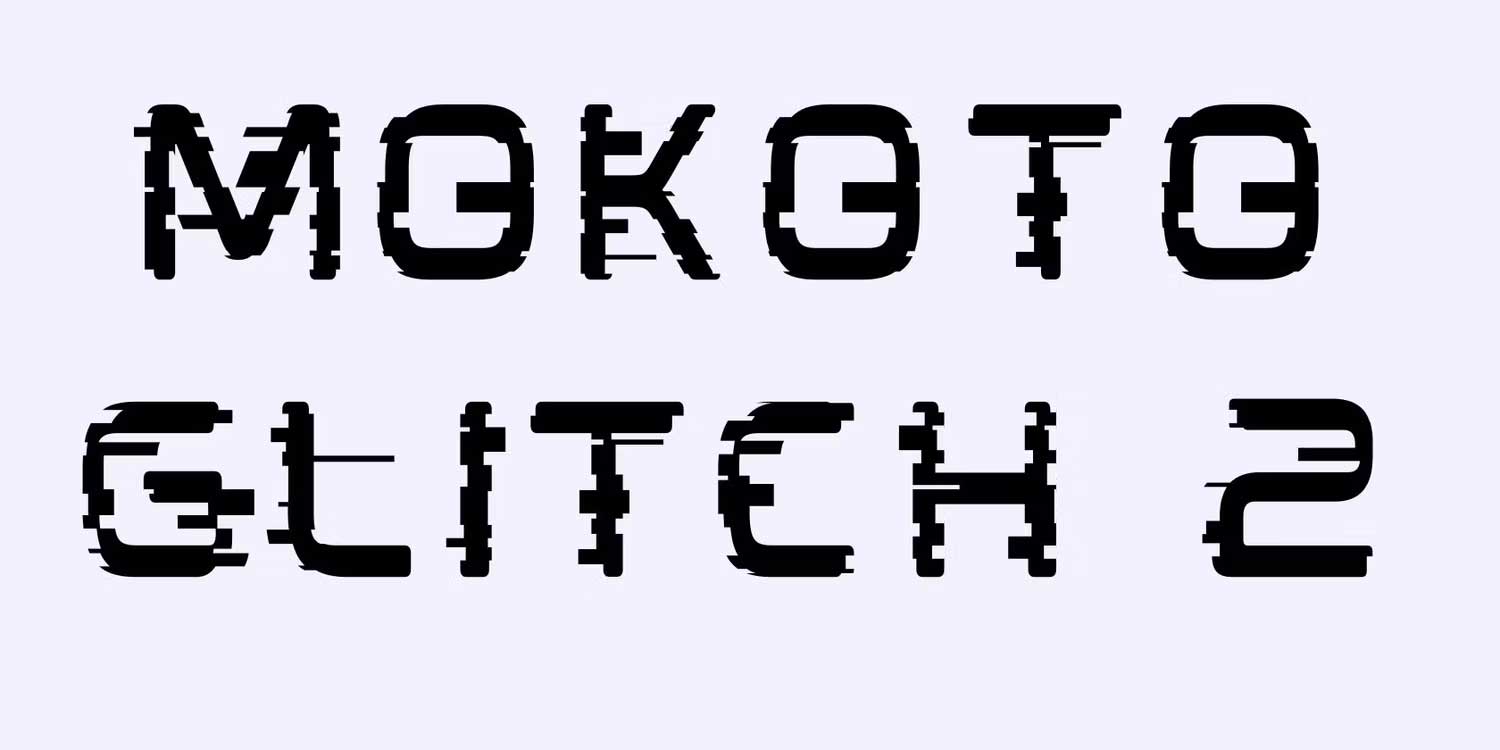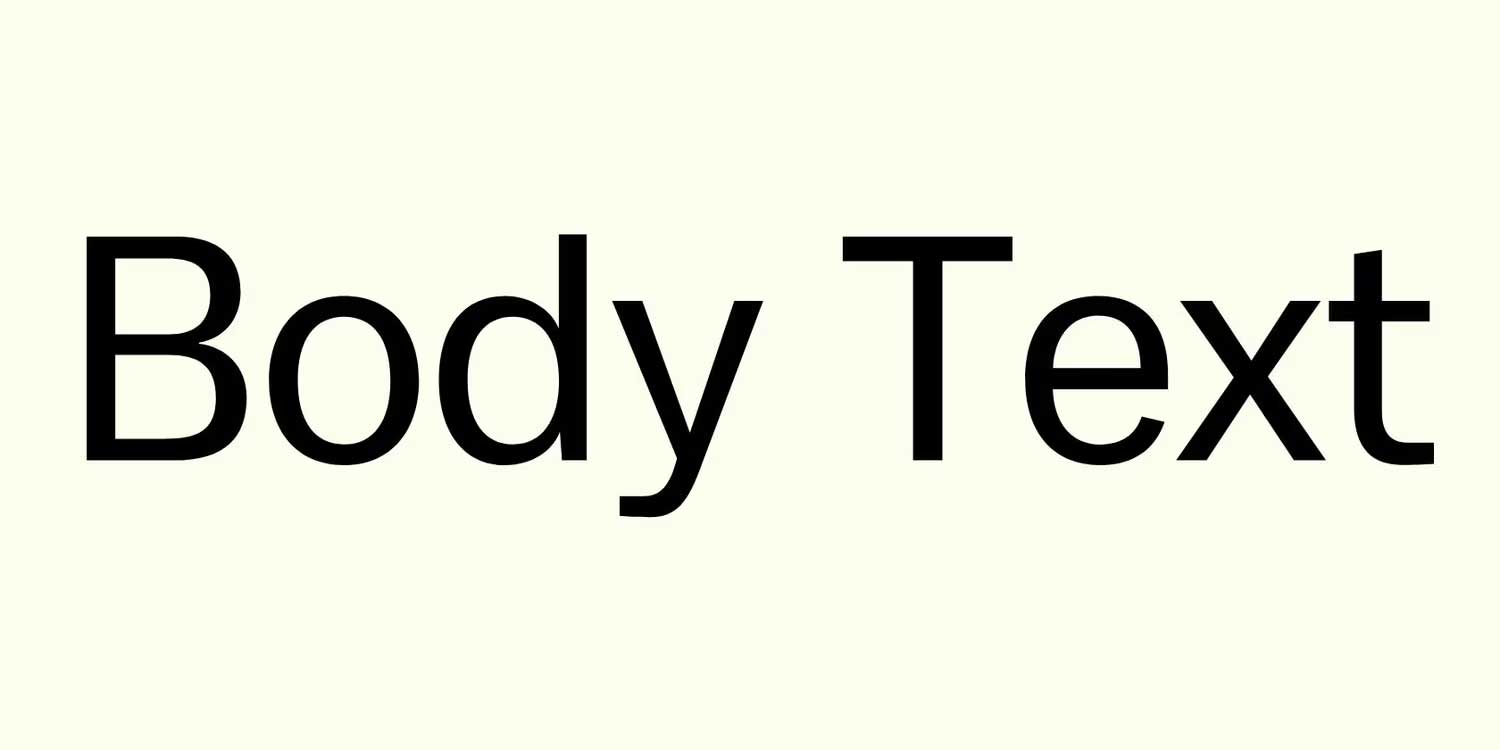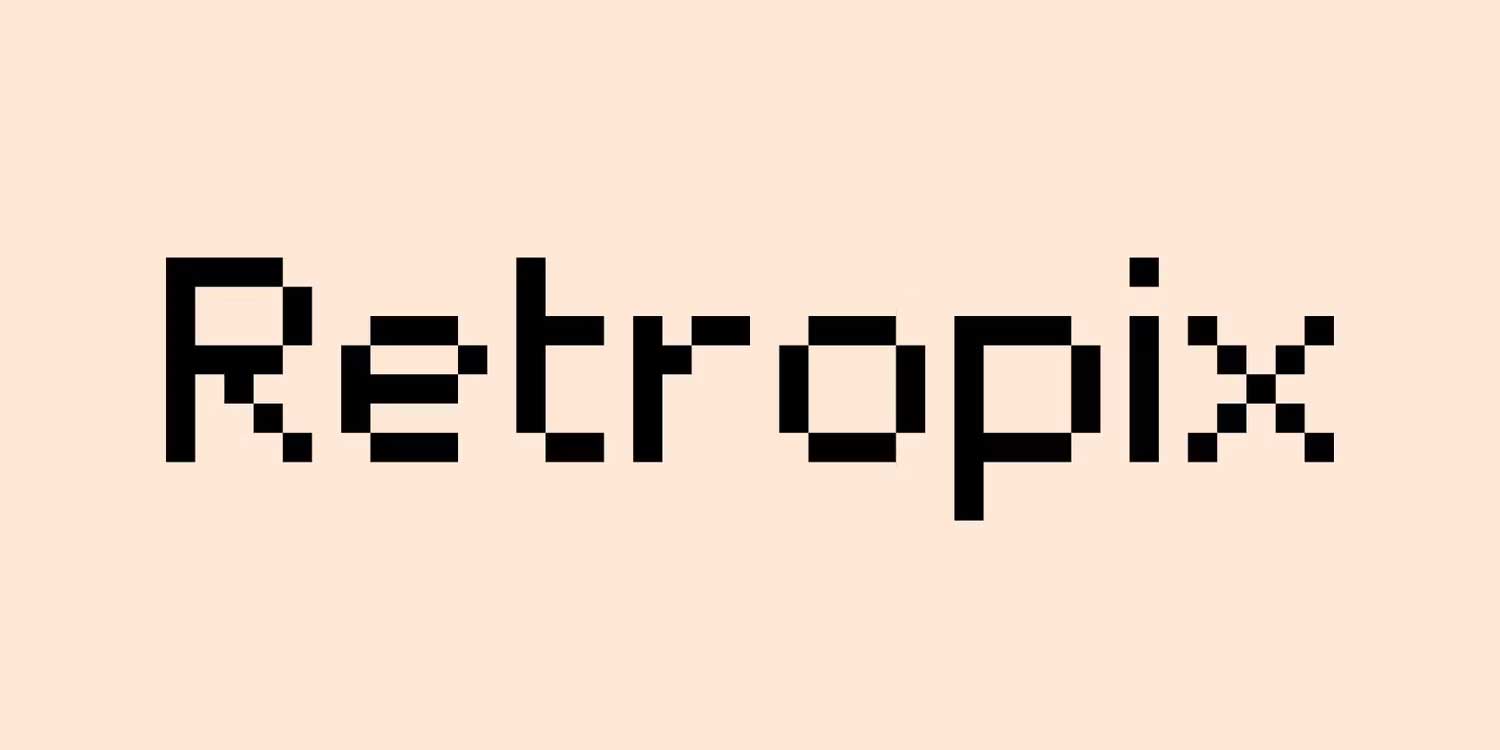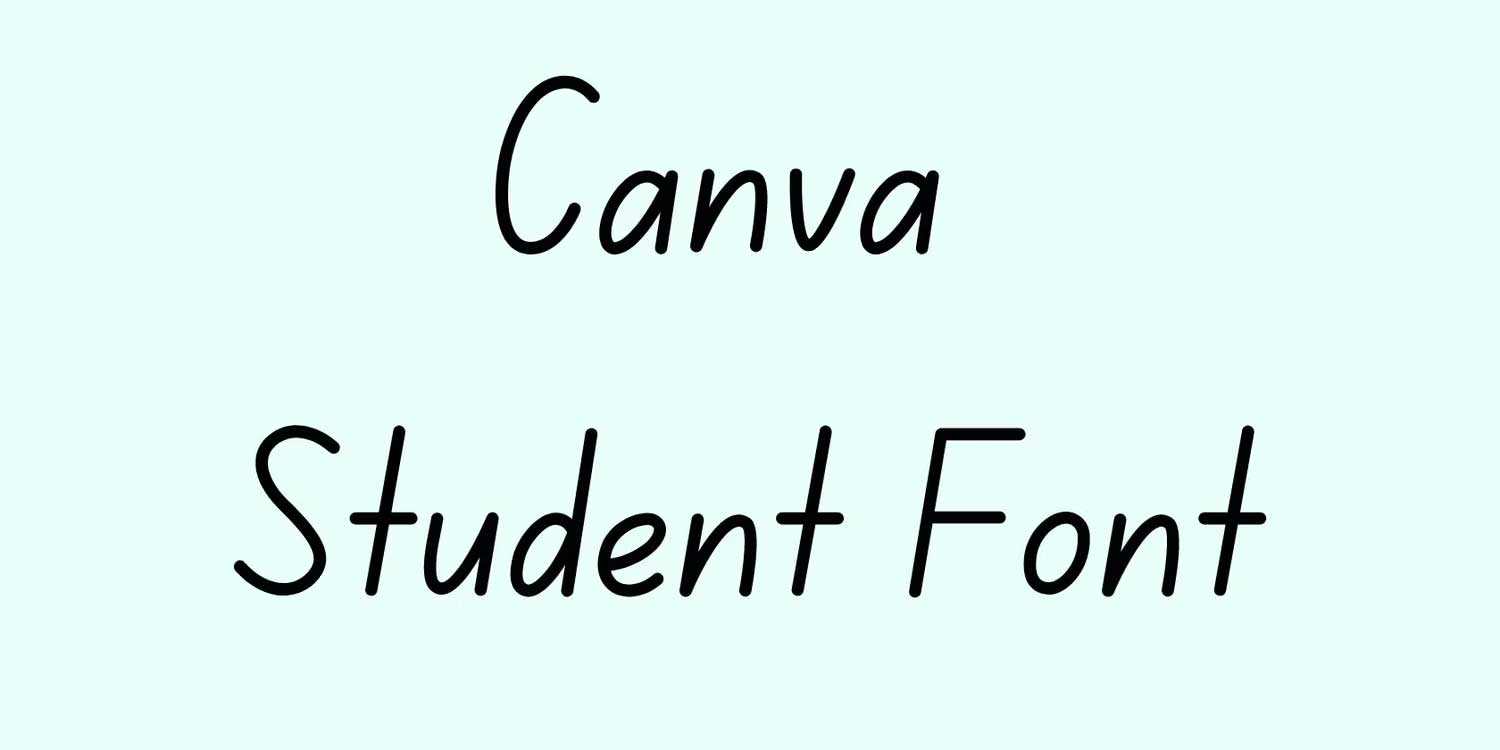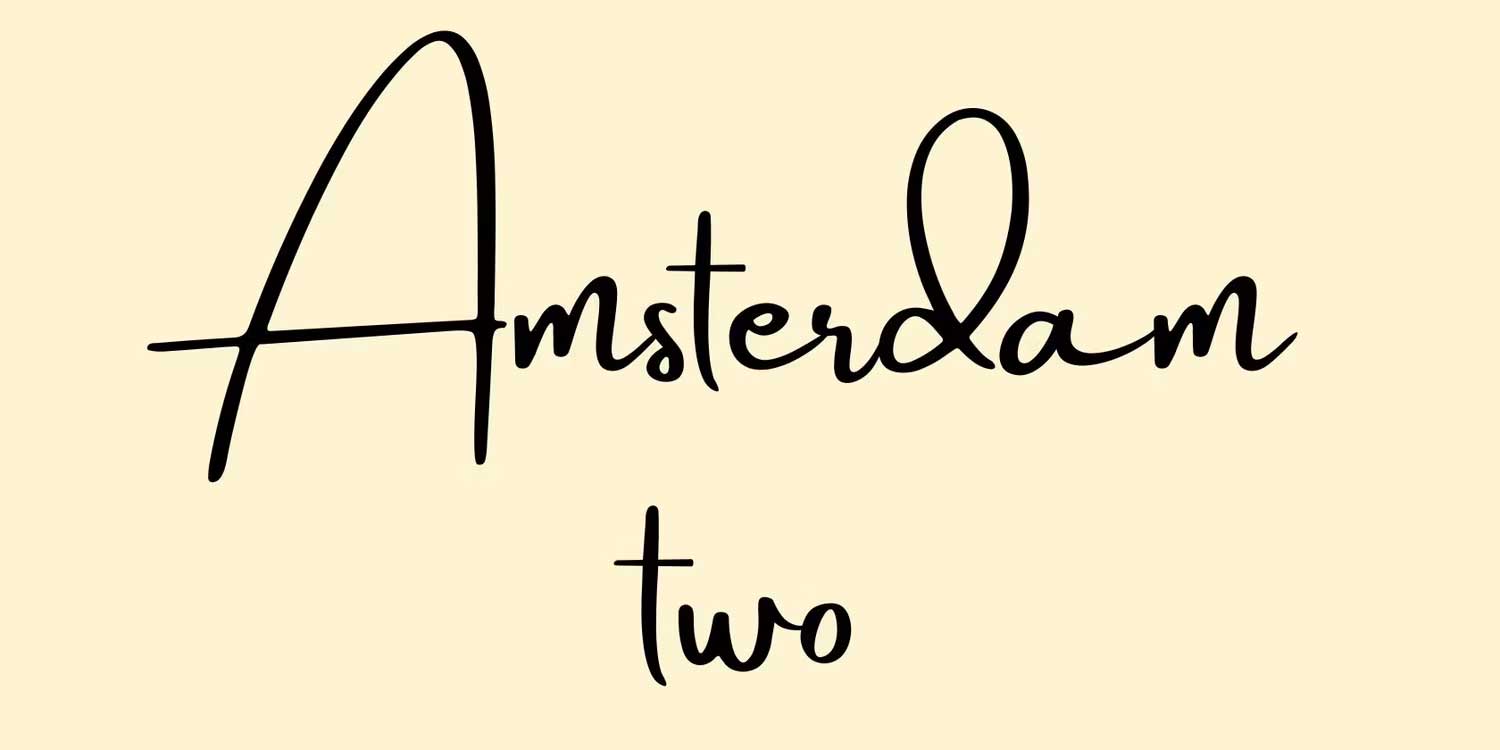
TOP font Canva miễn phí đáng dùng trong thiết kế và bài thuyết trình
Canva cung cấp cho người dùng rất nhiều font chữ miễn phí. Hãy cùng Download.vn liệt kê những font Canva miễn phí đáng dùng khi thiết kế và làm bài thuyết trình nhé!
BD Sans Thin
Font Canva BD Sans Thin
Nếu đang tìm kiếm một font cổ điển, đơn giản nhưng sang trọng trên Canva, BD Sans Thin là lựa chọn lý tưởng. Font Canva này không những đẹp mà còn có thể được ghép nối với một font chữ đậm như Notable để tạo hiệu ứng nhiều lớp.
Nếu muốn BD Sans Thin ấn tượng hơn, hãy tăng khoảng cách giữa các chữ cái.
MOKOTO GLITCH 2
Các font trang trí thỉnh thoảng có thể khó đọc nhưng MOKOTO GLITCH 2 vẫn dễ đọc, đồng thời, cung cấp hiệu ứng không đồng đều khá ấn tượng. Phông chữ Canva này đẹp mắt khi ở màu đen nhưng thậm chí còn tuyệt hơn khi được tô màu neon rực rỡ trên nền đen. Hãy thoải mái thử các hiệu ứng Glitch có sẵn trên Canva cho font này, bạn sẽ bất ngờ với kết quả đạt được.
Body Text
Body Text có thể không hoa mỹ, thú vị hay ấn tượng nhưng nó bù đắp thiếu hụt bằng tính thực tế. Những thiết kế tuyệt vời cho phần nội dung dễ đọc và đúng như tên gọi, font Body Text Canva được thiết kế cho mục đích này. Bạn sẽ có một kiểu font đẹp cho tiêu đề và đơn giản cho phần thân.
Retropix
Retropix là một kiểu font được nhiều người ưa thích bởi nó lạ mắt và thú vị nhưng vẫn dễ đọc ngay cả ở kích thước nhỏ. Đối với nội dung dựa trên công nghệ hay bất cứ thứ gì bạn muốn thêm điểm nhấn retro, Reptropix là lựa chọn hoàn hảo. Nếu muốn đưa Retropix lên cấp độ mới, hãy thử hiệu ứng Canva Glitch.
Canva Student Font
Canva không thiếu font chữ viết tay, nhưng hơi khó tìm font có thể đọc. Canva Student Font là font chữ viết tay tuyệt vời cho văn bản bạn muốn có thể đọc dễ dàng. Nó đơn giản nhưng vẫn mang đậm dấu ấn cá nhân, phù hợp với phần thân bài.
So với các kiểu chữ viết tay như Apricots, Canva Student Font không lạ mắt bằng nhưng nó thực tế, có thể dùng trong nhiều trường hợp.
Amsterdam Two
Font Canva Amsterdam Two
Đúng như tên gọi, Amsterdam Two chỉ là một font trong chuỗi phông chữ đặc biệt trên Canva. Nó bao gồm 4 font Amsterdam khác nhau.
Khác Canva Student Font, Amsterdam Two thực sự làm nổi bật các chữ cái in hoa, khiến tiêu đề ngắn trở nên tuyệt vời.
• Trên đây là những font Canva miễn phí, đáng dùng nhất khi thiết kế hay làm bài thuyết trình. Hi vọng bài viết hữu ích với các bạn.